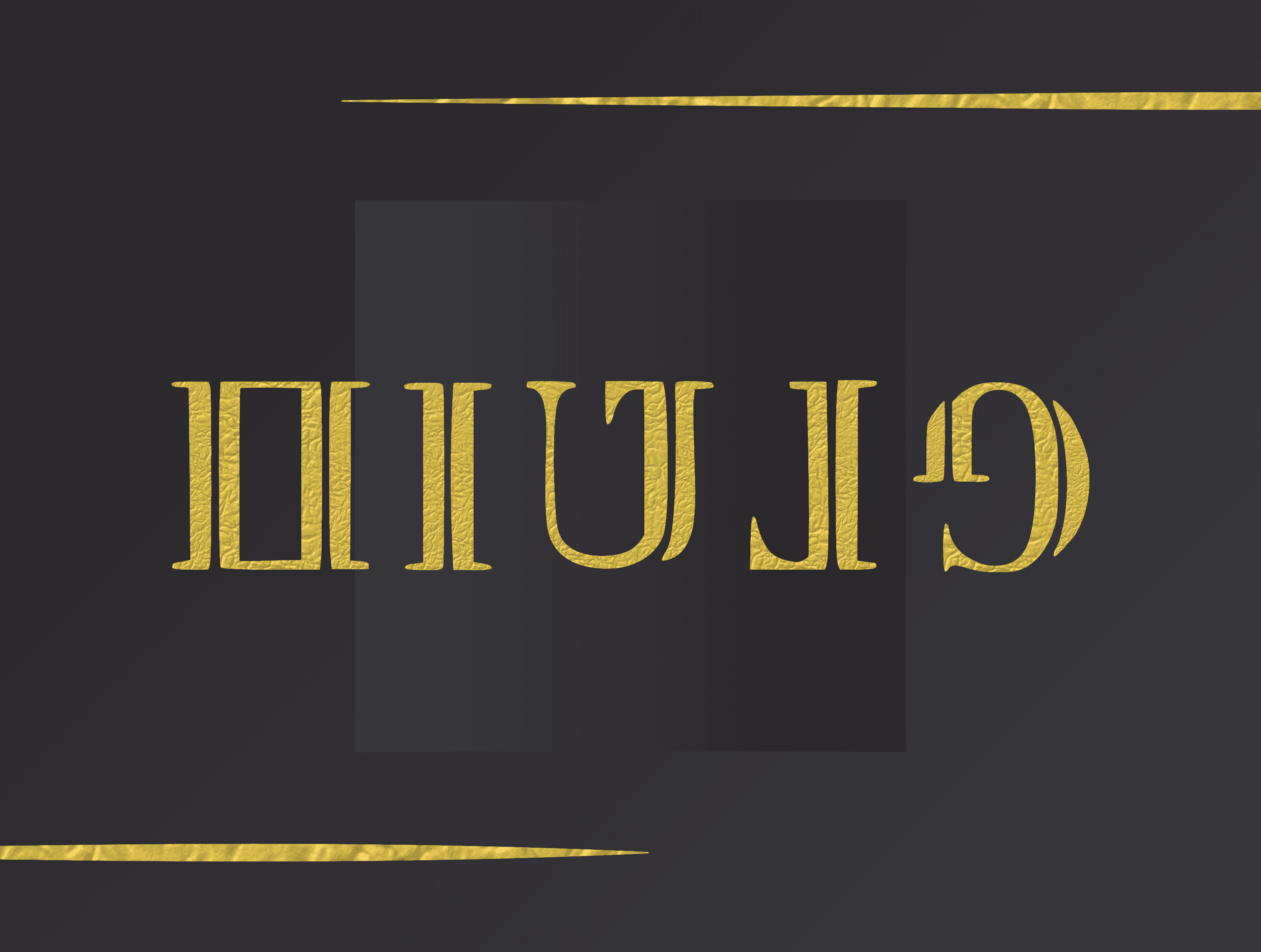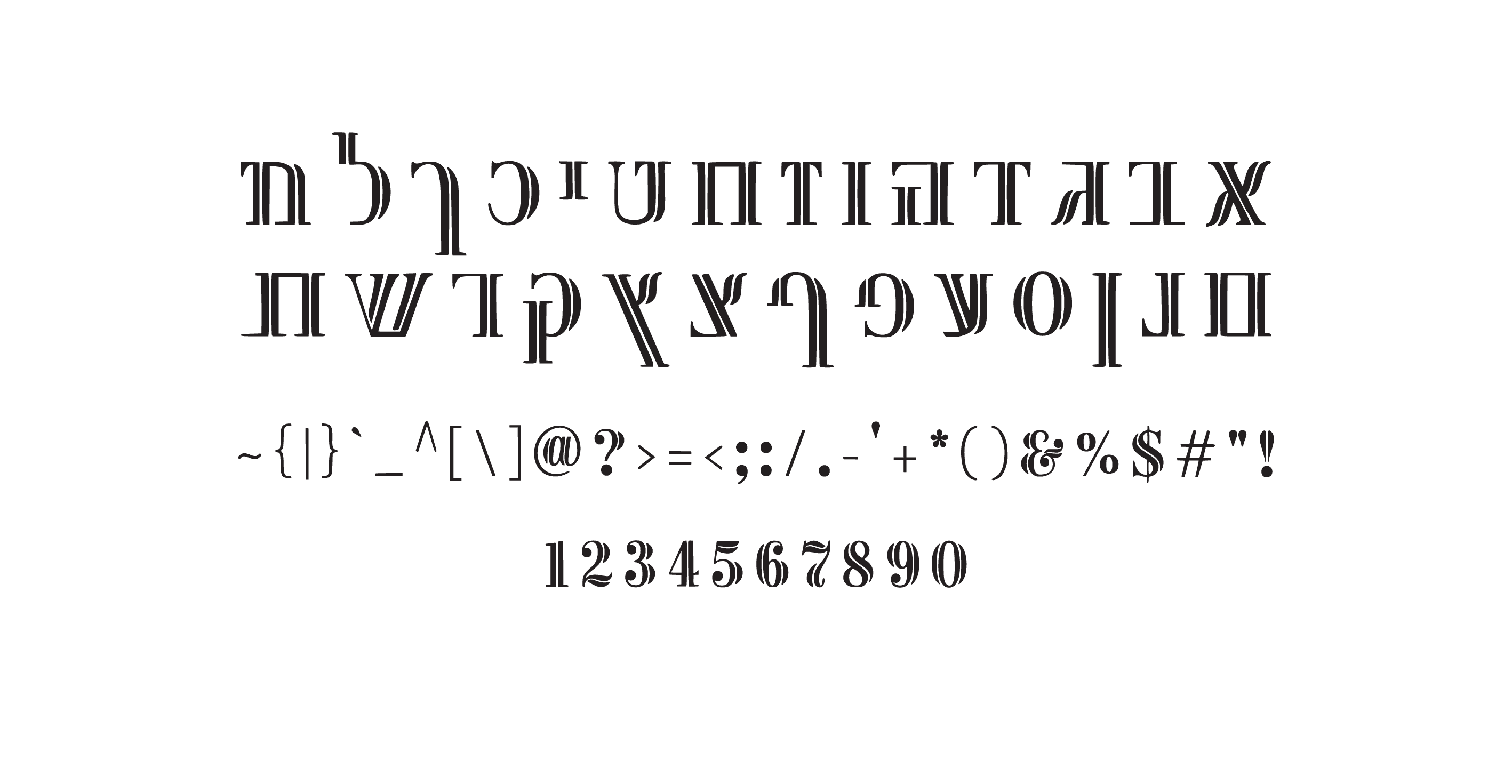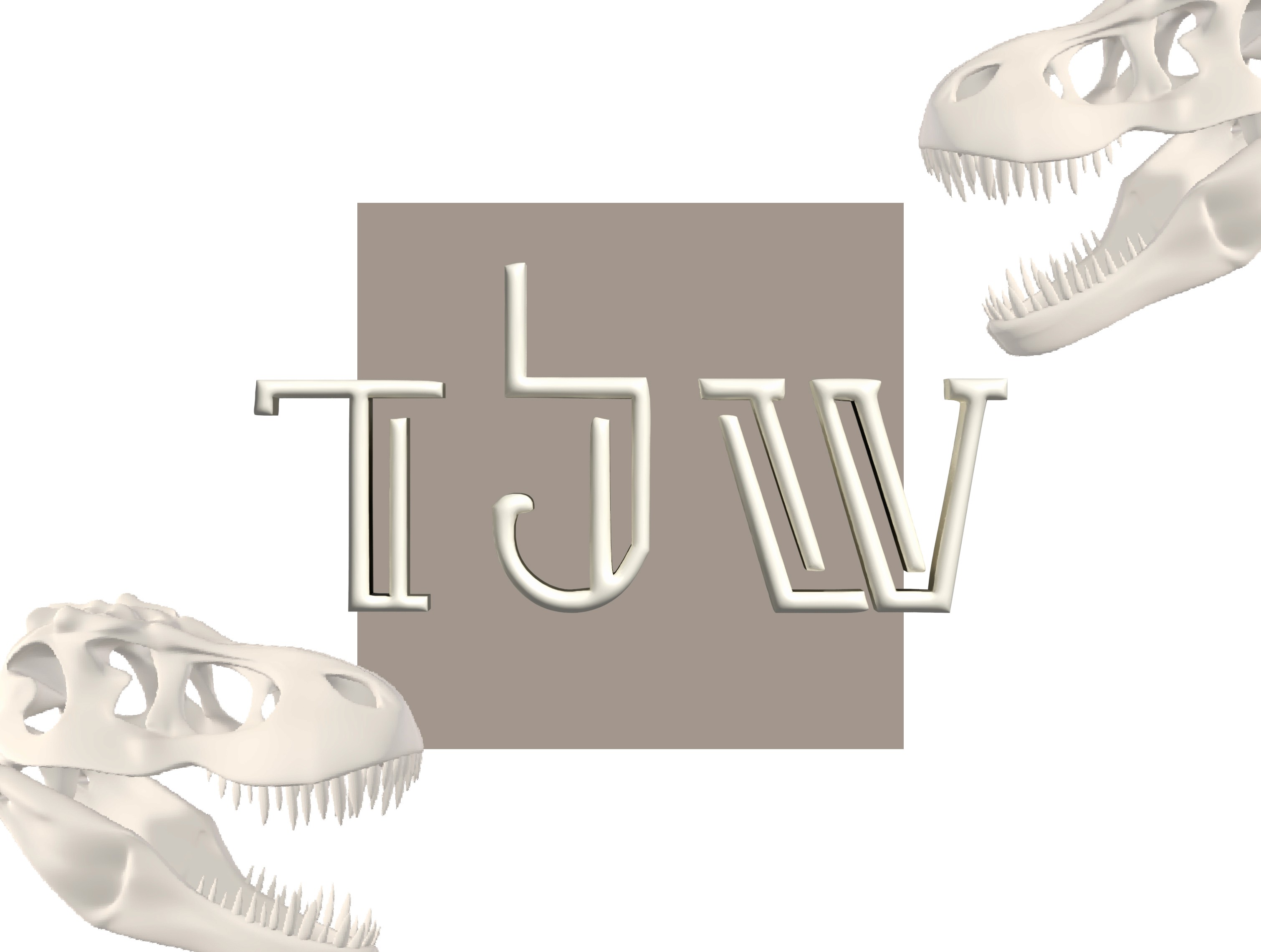
פונט פנטום
פונט בעל אופי דרמטי ומסתורי, בהשראת עולם התיאטרון והאשליות, עם קווים ייחודיים ונוכחות בימתית.
פונט פנטום נולד מתוך געגוע לתקופות בהן כל אות נשאה סיפור.
זהו פונט בעל נוכחות חזקה, עם צללית דרמטית ומסתורית, שמתאים בדיוק למיתוגים שרוצים לשדר אלגנטיות, עומק ורושם בלתי נשכח.
האותיות מעוצבות בהשראת פוסטרים של תיאטראות ישנים ועטיפות ספרים מסתוריים, עם משחקי קווים חדים ומעוגלים שיוצרים יחד קומפוזיציה מרתקת.
מתאים לשימושים בולטים כמו:
כותרות גדולות ומרשימות
עיצובי פוסטרים וקאברים
פרויקטים בעלי אופי אפלולי, מסתורי או דרמטי
מיתוגים שמבקשים לשדר קלאסיקה עם טוויסט מודרני